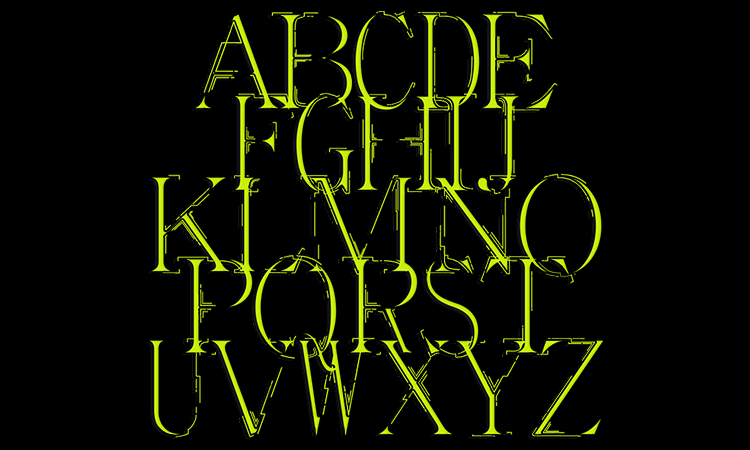
Outer Space 2019.03.24 2016.12.05Outer Spaceは、ユニークなデザインの英語フォントです。ガタガタとしたラインが特徴ですが、ある程度の規則性があり全体としての統一感があります。ライセンス無料で使える商用可のフリーフォントです。ダウンロードOuter Space当サイトはフリーフォントの紹介サイトです。フォントを利用の際には、各サイトで最新の利用条件やライセンスを必ず確認してください。フォント情報ライセンス商用可カテゴリー日本語 > ユニークタグかっこいい、ユニーク、エキセントリック、ラフ